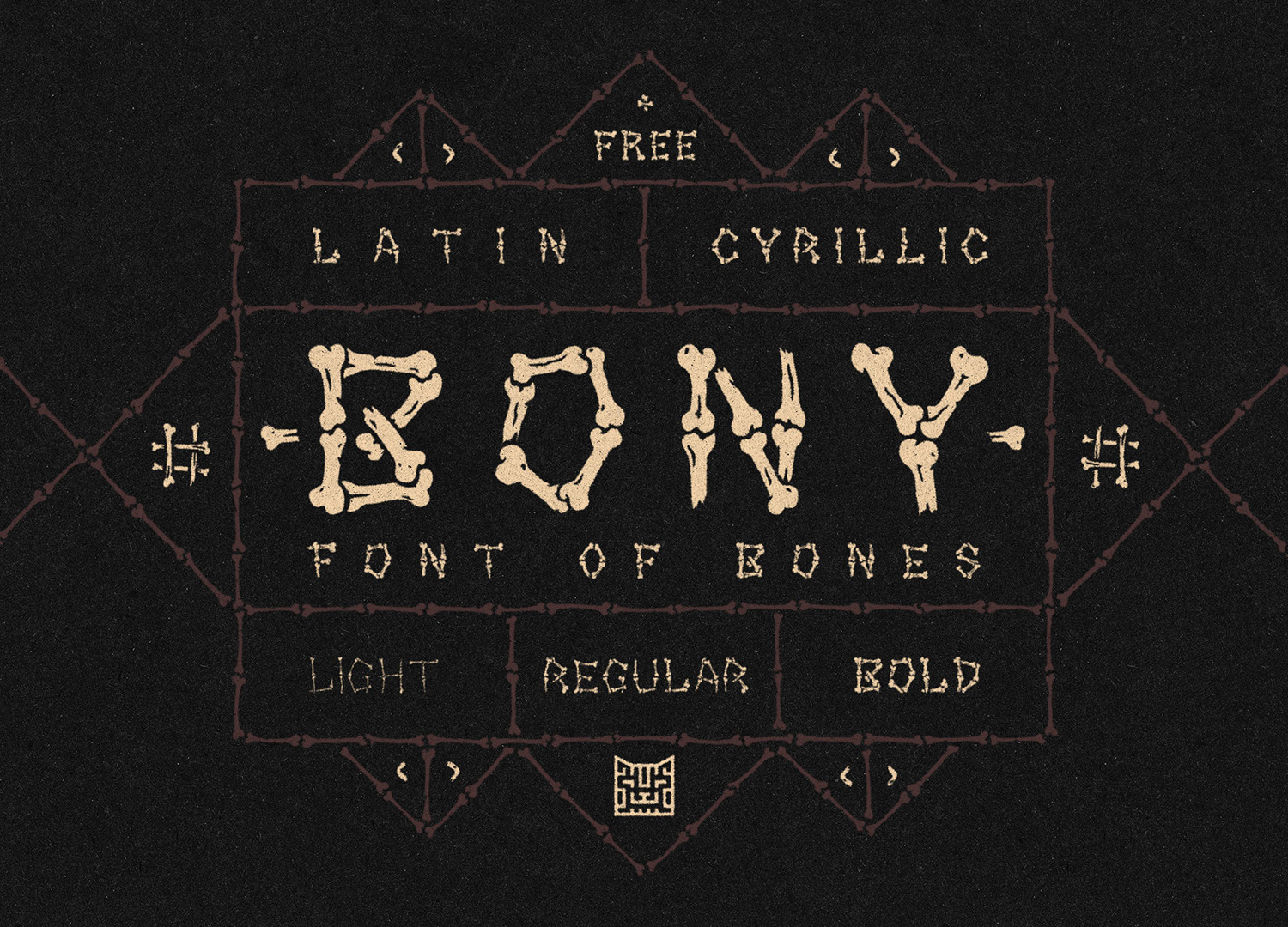
Шрифт в форме косточек. Кириллица
Костлявый шрифт для твоих проектов) Идеально под хорор тематики. Для декоративного шрифта он имеет хорошую читаемость) Автор: 2DFUNS. Текущее начертание бесплатно.